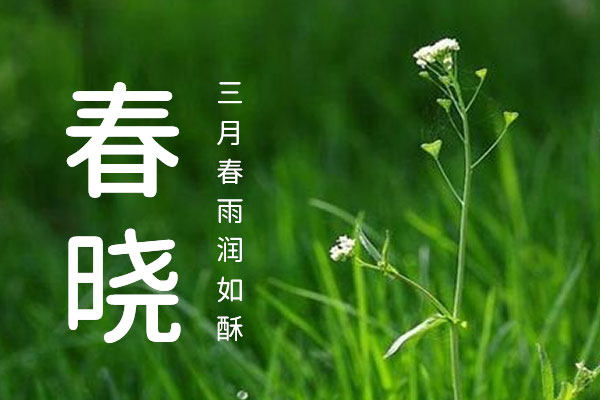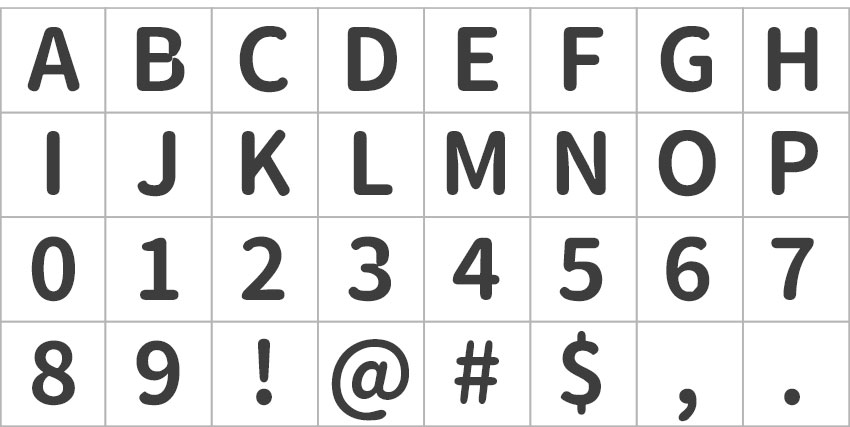
资源圆体
在免费商用的圆体字型中,除了广为人知的源柔黑体(国内常称为“思源柔黑”),还有一款字体值得推荐——资源圆体。资源圆体是中国设计师Cyano Hao基于中国版的思源黑体改造而成的。
资源圆体(Resource Han Rounded)是思源黑体的一个变种,其特征与思源黑体基本一致,因此它对简体中文的支持非常好,不会出现缺字现象。与思源黑体一样,资源圆体也拥有7个字重,能够满足大部分设计需求,压缩包里有7个字重文件,所以体积大一点,选择适合您的字体即可。
资源圆体效果预览
资源圆体字体效果预览